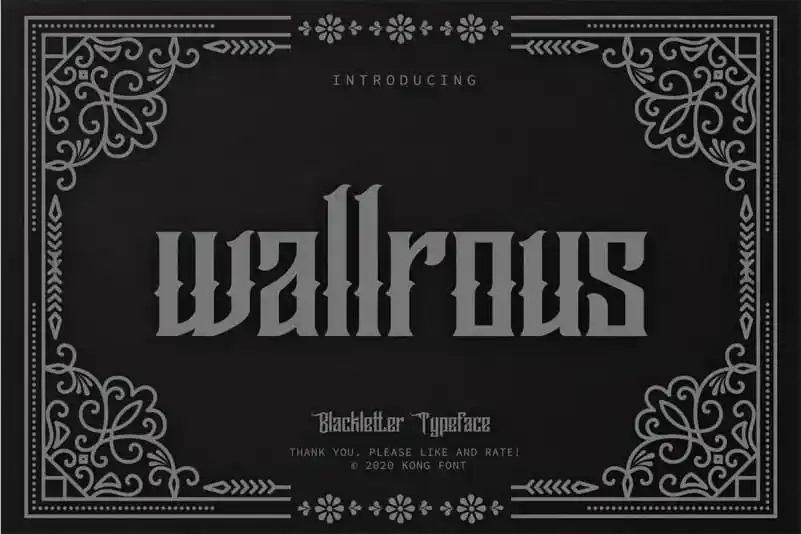
Descubra a Wallrous Blackletter Font, uma poderosa escolha para projetos que valorizam estilos antigos e elegantes. Essa fonte blackletter é notável por sua originalidade e característica sofisticada, tornando cada projeto design com esse estilo perfeito e impecável. Esta fonte, criada pelo site de criação de desenhos 99designs, traz uma atmosfera única que enriquece qualquer trabalho gráfico. Suas linhas elegantes e detalhes únicos a tornam um recurso ideal para designers em busca de adicionar um toque de estilo clássico às suas produções digitais. Seja para editoriais, logos ou materiais publicitários, a Wallrous Blackletter Font é uma opção inovadora que certamente será o complemento perfeito para seu trabalho gráfico.